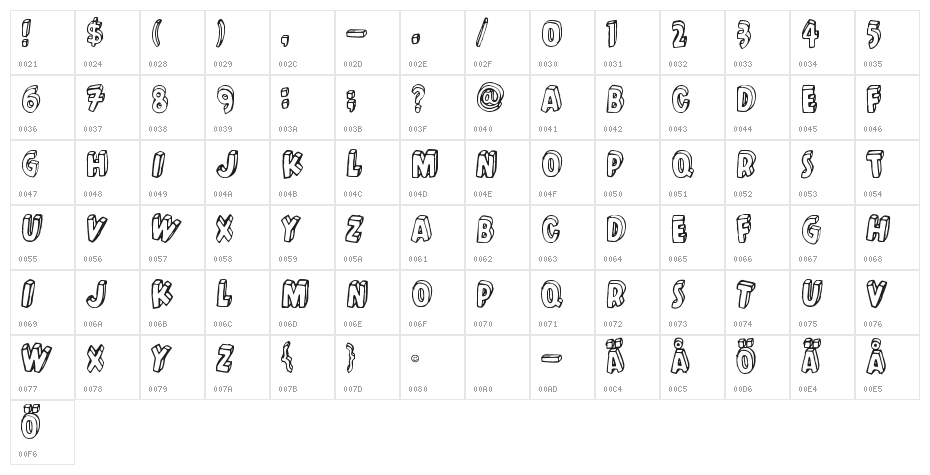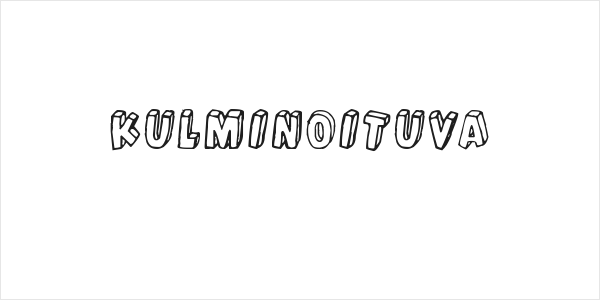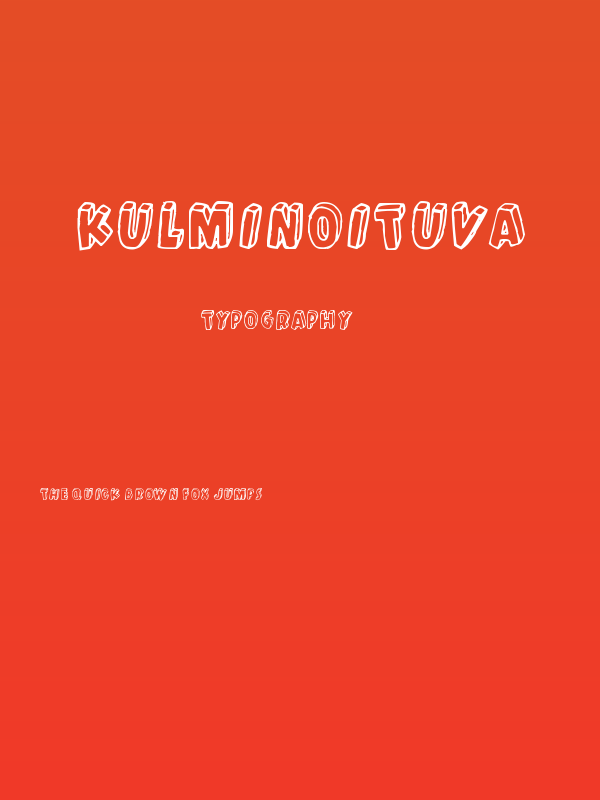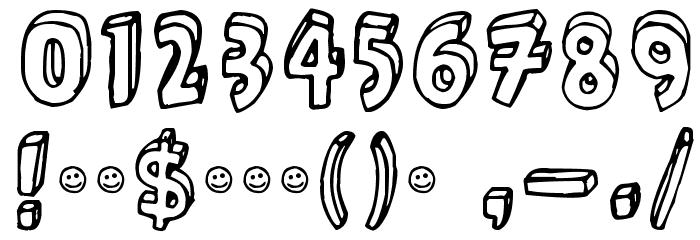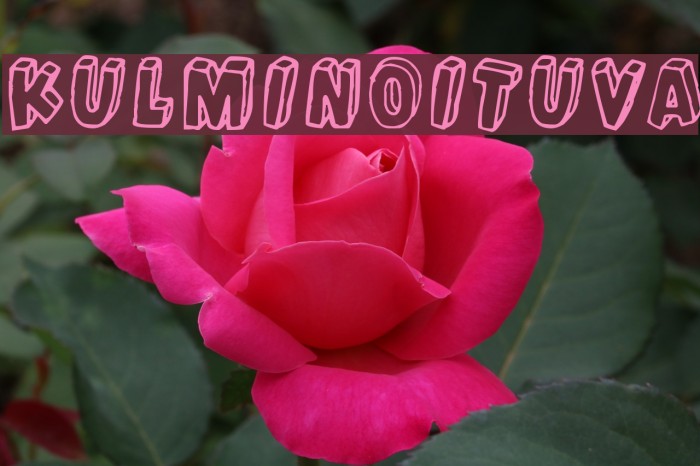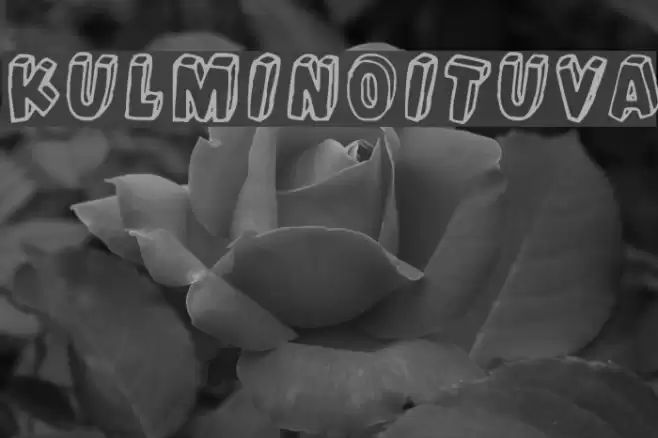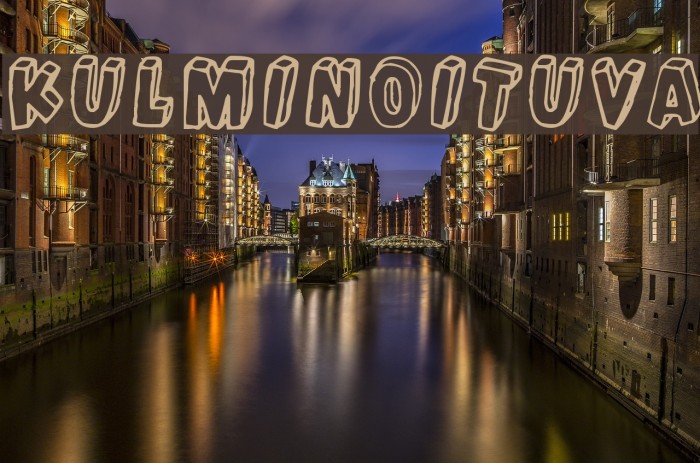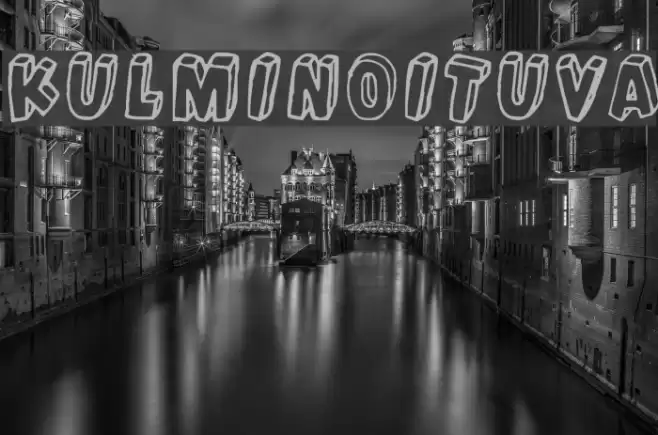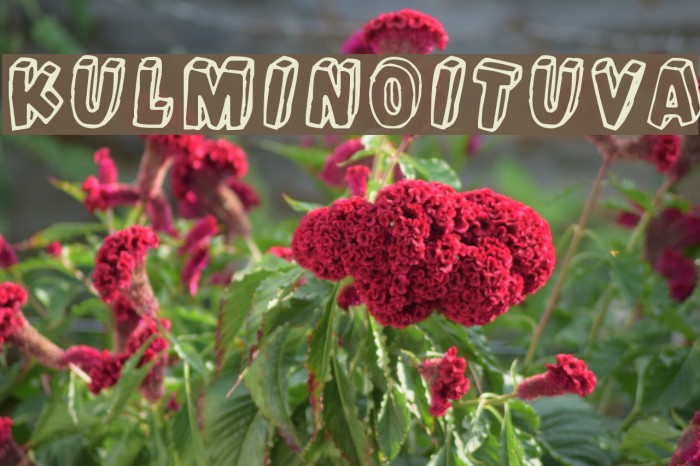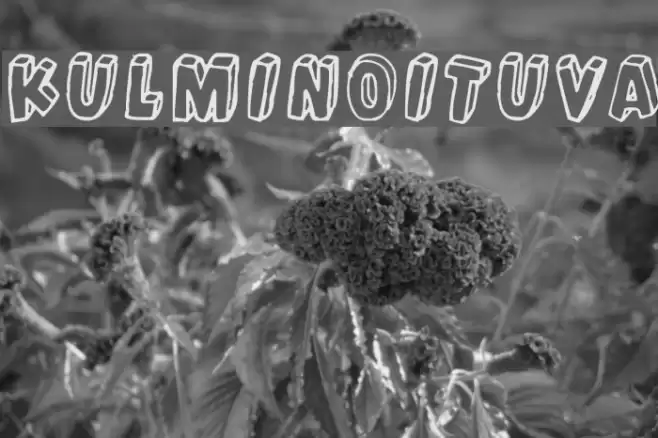
Kulminoituva Font
| النمط العام | Playful, Cartoonish, Hand-drawn |
| مشاريع مقترحة | Ideal for children's books, comic strips, playful branding, posters, and creative invitations. |